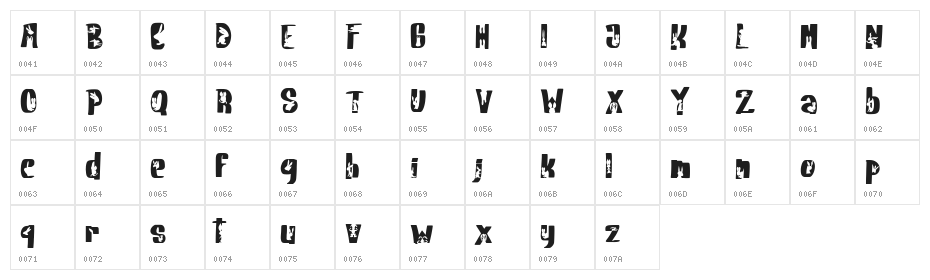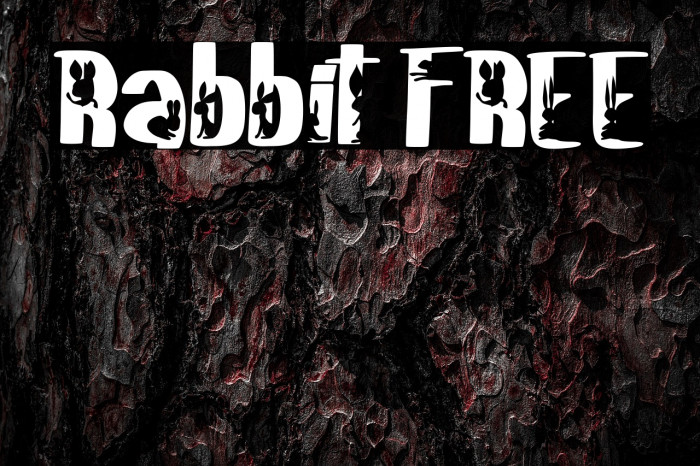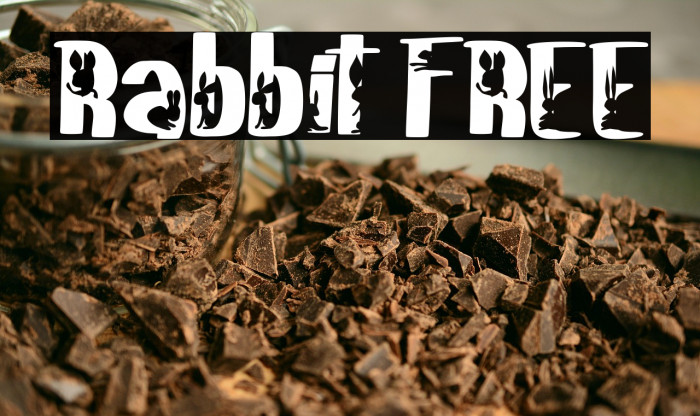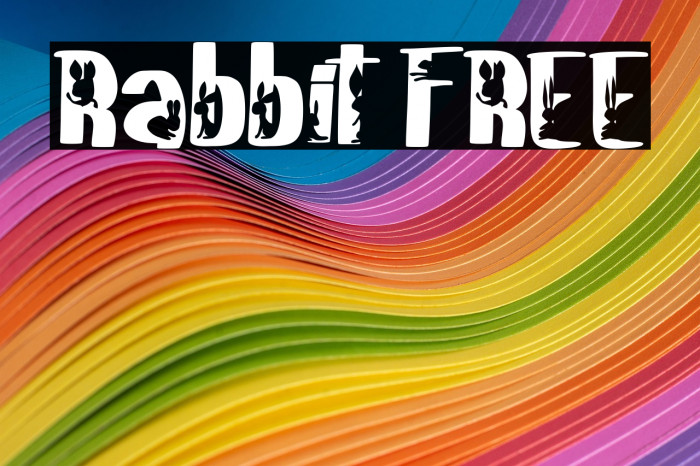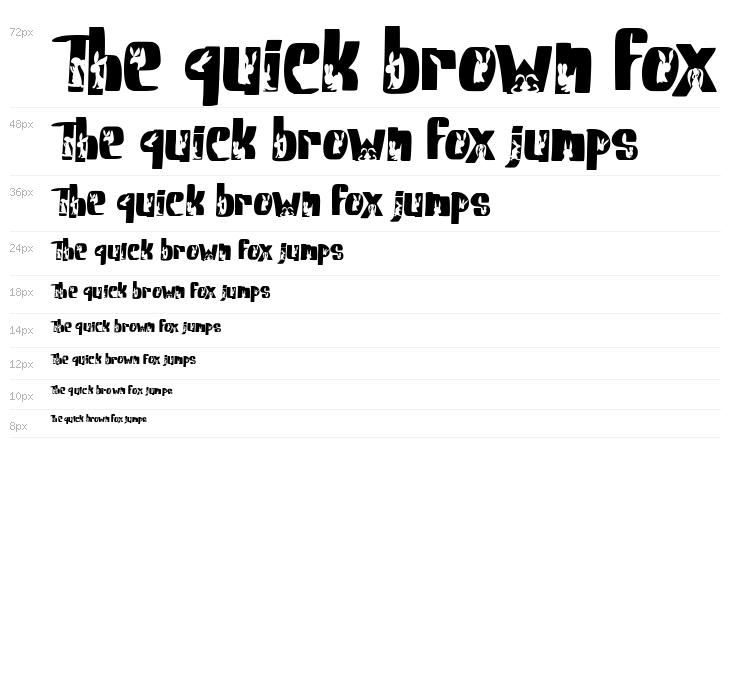
Rabbit FREE Font
| Gesamtstil | Playful, Whimsical, Decorative |
| Vorgeschlagene Projekte | Children's books, playful branding, greeting cards, posters, and whimsical designs. |